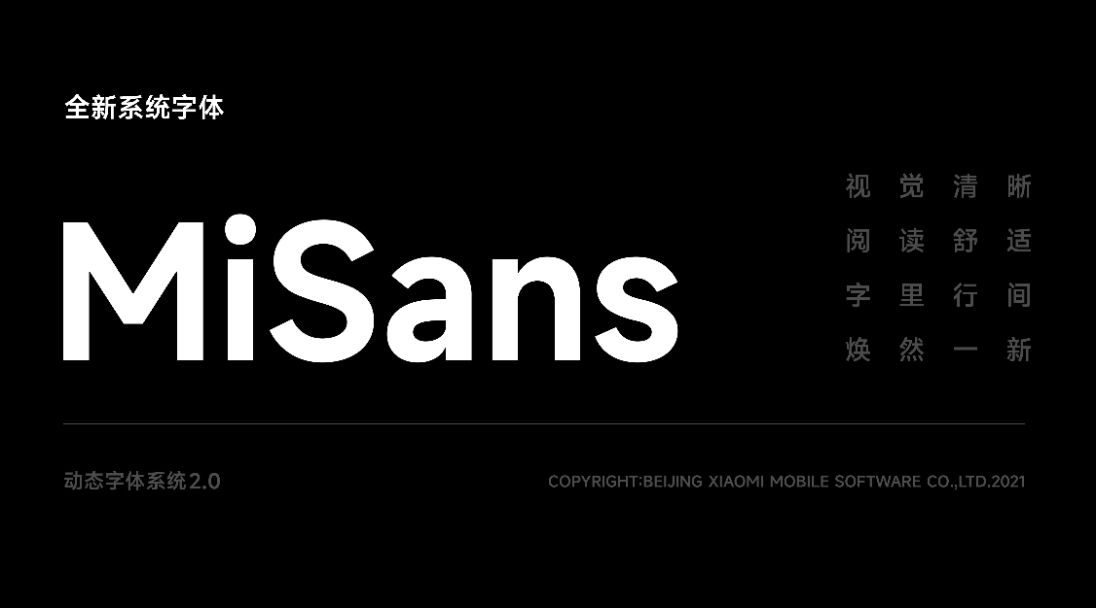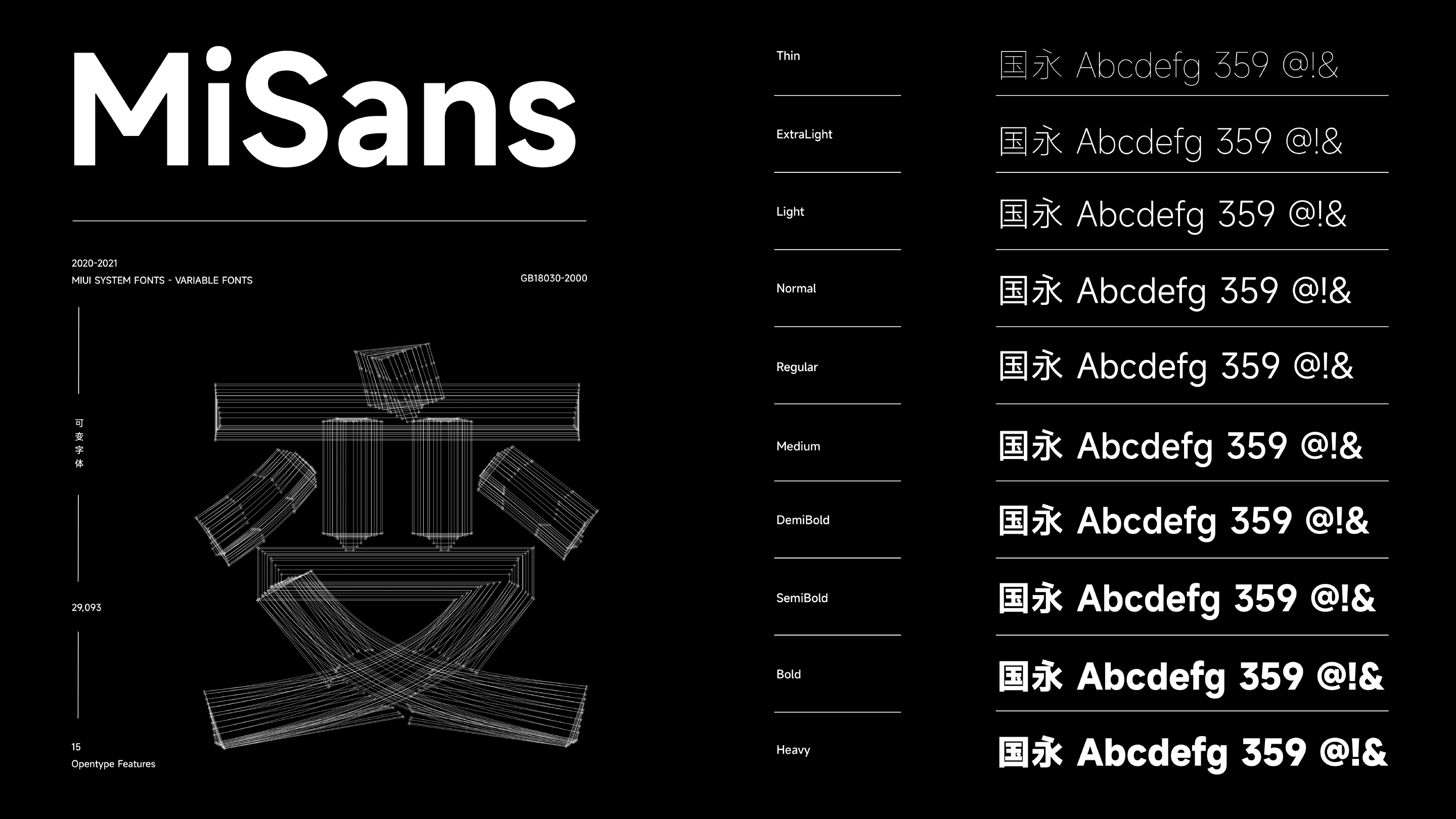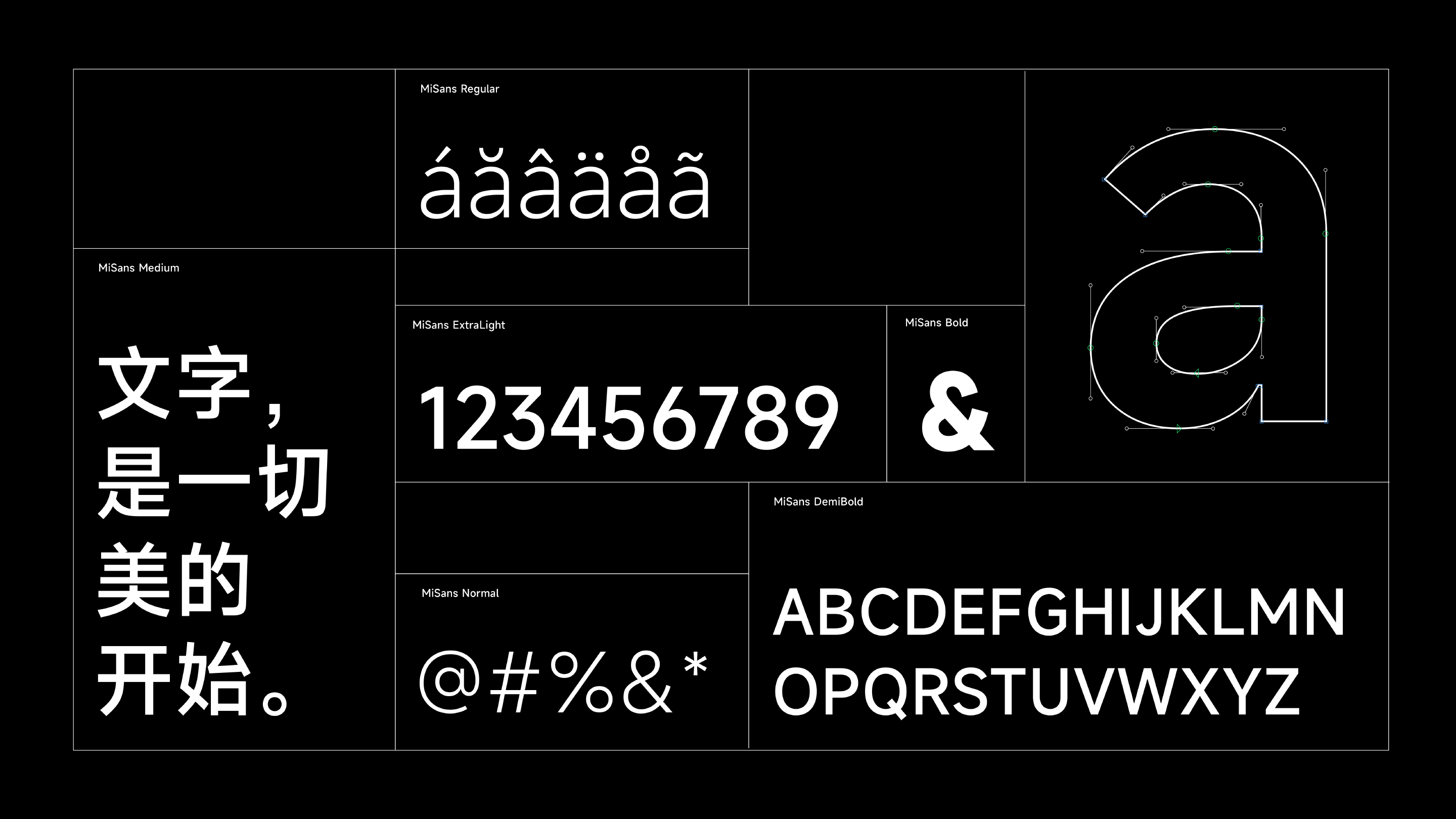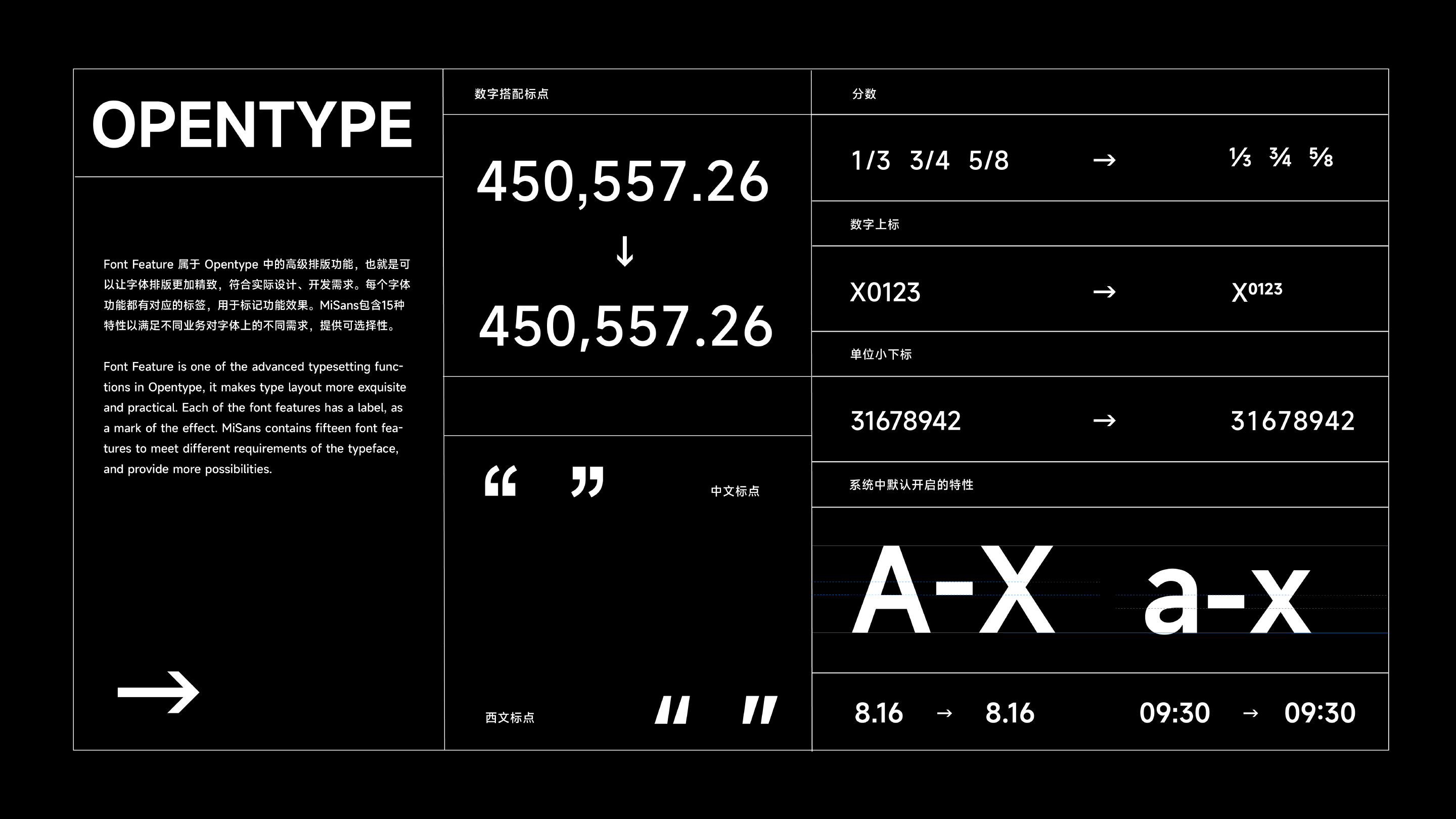
MiSans 是全新系统 MIUI 13 的默认字体;
MiSans笔型平直有力,设计更加简约,减少视觉负担,更有利于屏幕显示。共包含29,093个字符,支持多种语言。
MiSans 提供了多种 OpenType 功能,可根据特定需求来选择不同形态的字符,例如某些标点符号可以根据周围字母的形态自动调整至合适的位置。
MiSans字重齐全,层级清晰,10个字重全部开放下载,供全社会免费商用。